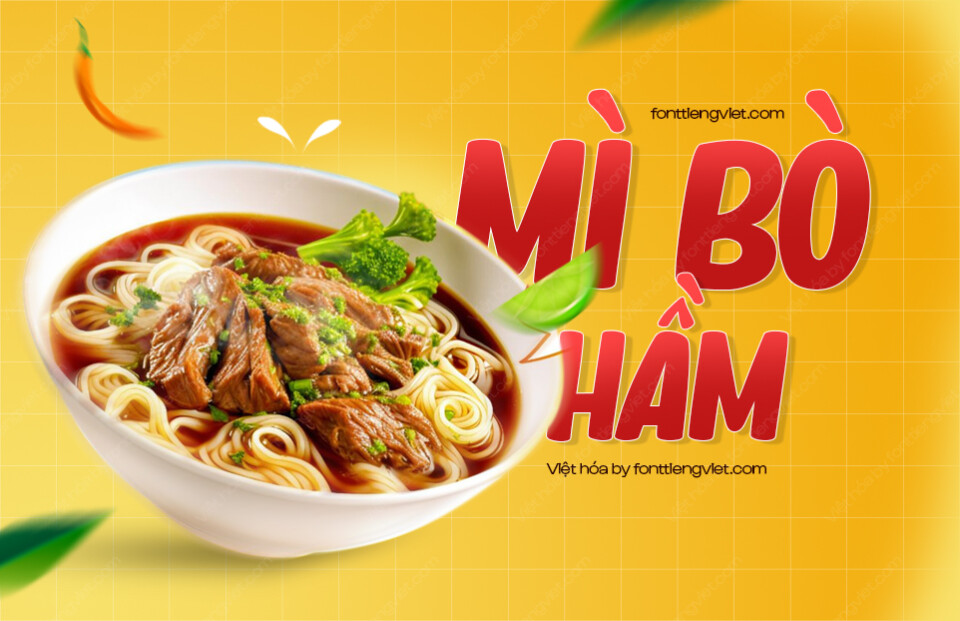
Font Việt hóa TF Rogbold Việt Hóa
Font Việt hóa TF Rogbold
Tên font: Font Việt hóa TF Rogbold
Tác giả: FontVietHoa.Org
Font Việt hóa TF Rogbold là một font Việt hóa có nét đậm, đường nét thiết kế tinh tế.
Font phù hợp với các thiết kế tiêu đề nổi bật, gây chú ý.